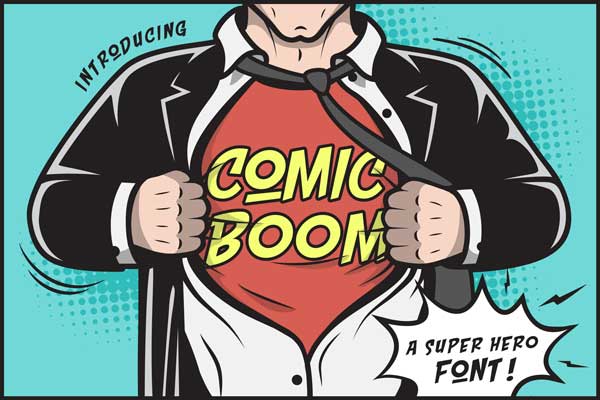
Comic Boom یک فونت بسیار جذاب و زیبا است که مناسب طرح های کامیک (کتاب کمیک) میباشد. این قلم زیبا و حرفه ای توسط Font Bundles Store طراحی شده است و با قیمت 10 دلار بفروش میرسد که نسخه جدید و نهایی این فونت فوق العاده را میتوانید بصورت کاملا رایگان و با یک کلیک از نال اکس دریافت نمایید.
- مناسب برای انواع طرح های گرافیکی
- مناسب برای ساخت و طراحی فونت، پوستر، لیبل و …
Comic Boom is a comic style font, perfect for any superhero projects!